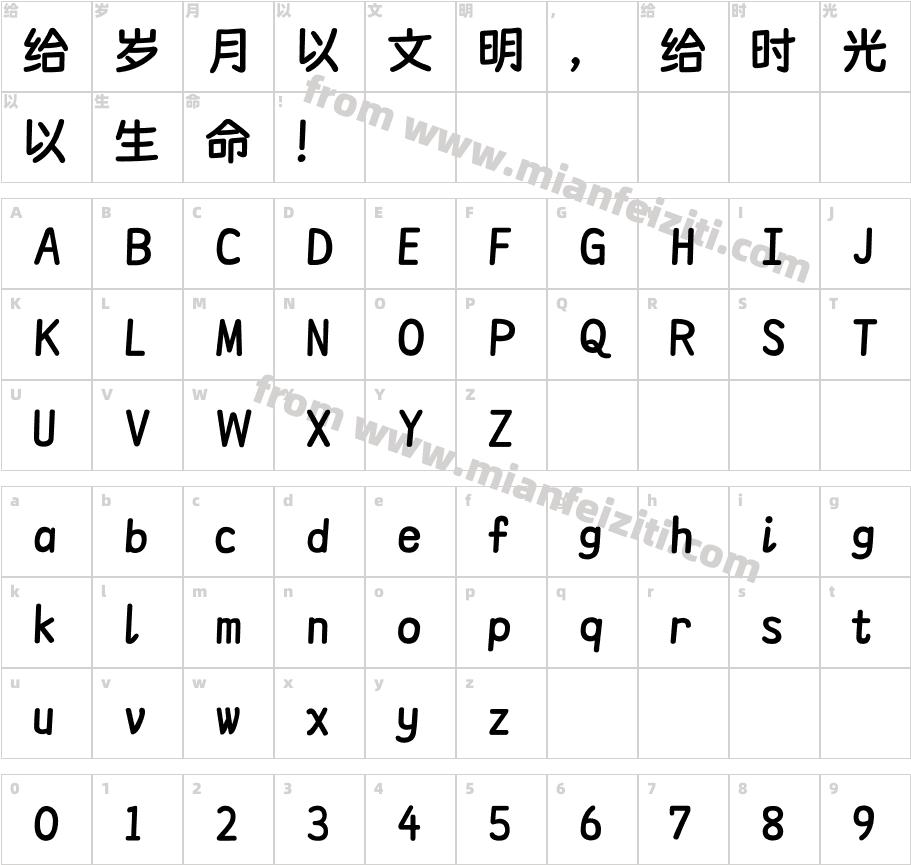
荆南麦圆体
字体名称: 荆南麦圆体
荆南麦圆体预览图1
不知道大家用荆南缘默体用得怎么样?用得爽不爽?告诉大家一个好消息,荆南缘默体的作者@荆南字坊又有新作啦!荆南麦圆体历经半年的肝夜紧张制作,终于发布测试版啦,其可爱的字型还是让人爱不惜手。
荆南字坊麦圆体的设计灵感来源于韩国的一个综艺节目上的谚文字体,手写的风格圆润的笔画让这款字体看起来很可爱。
麦圆体萌系可爱的手写风格,字体每个笔画的粗细相同,两端圆润饱满,凸显可爱风格。虽是手写字体,笔画分明没有细小的连接,使字体更加清新俏皮。无论是做食品类还是母婴类,抑或是儿童类的设计都特别适合。
横画略偏斜,日字不封口,接近手写特征尾端圆润,横竖均一,保留趣味性的同时可读性高,也能适应屏幕显示。
荆南麦圆体预览图2
荆南麦圆体字体映射图